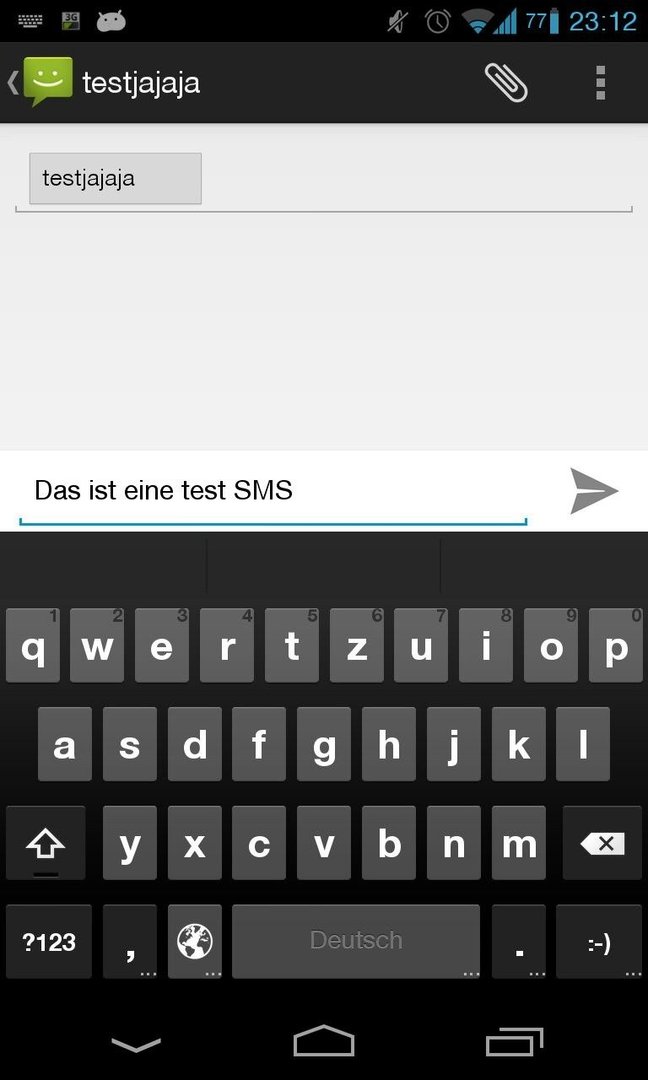
Ich kann dir Helvetica Neue anbieten. Wenn du mir dafür die flashbare .zip erstellst, dann wäre ich dir 1000x dankbar :)
Gerne, kannst die schriften gezippt aber auch gerne hier hochladen
Bei mir ist die Schrift etwas verzerrt. In deinem Beispiel sieht das sauberer aus?
Weißt du vielleicht an was das liegt?
Screenshot angehängt.
Is mir auch aufgefallen. Vorallem die a's. Ich gab keine Ahnung, muss an der font an sich liegen. Ich benenne sie nur in Roboto-... um. Evtl. wäre n bischen größer oder kleiner besser. Kann morgen mal nach alternativen googlen.
Ist es möglich dass auch die Bold fonts getauscht werden? Das heißt dass auch dann dicke schriften zB in helvetica dargestellt sind?
Die können ersetzt werden, wenn entsprechende Schriften vorliegen:
+ 4 neue Schrifarten (leider 2 nur mit einer font datei)